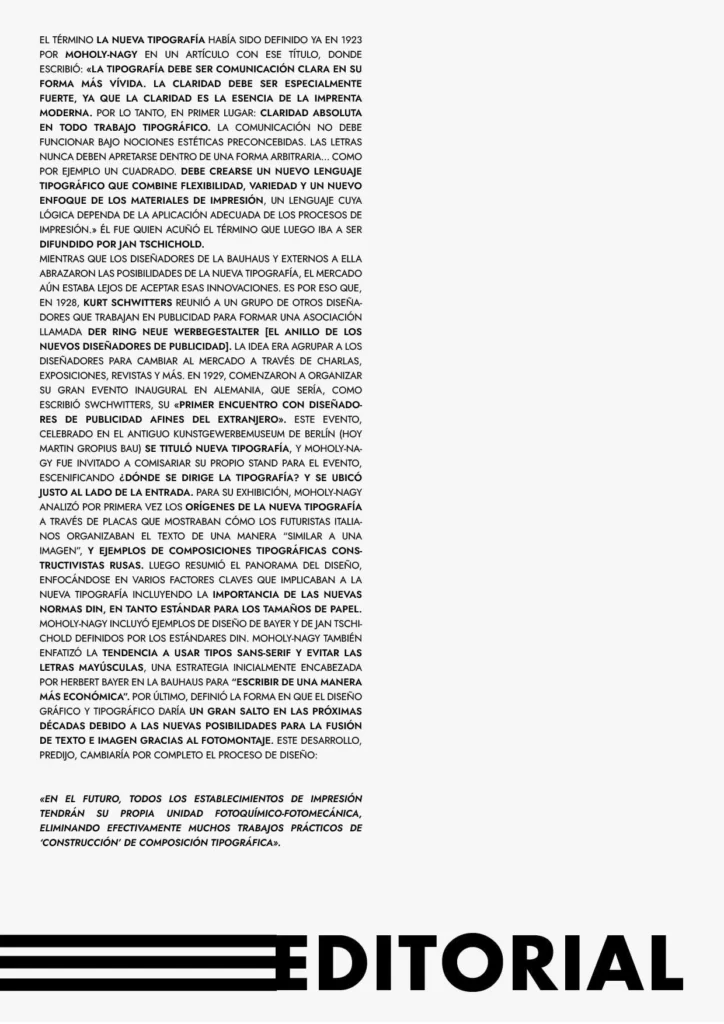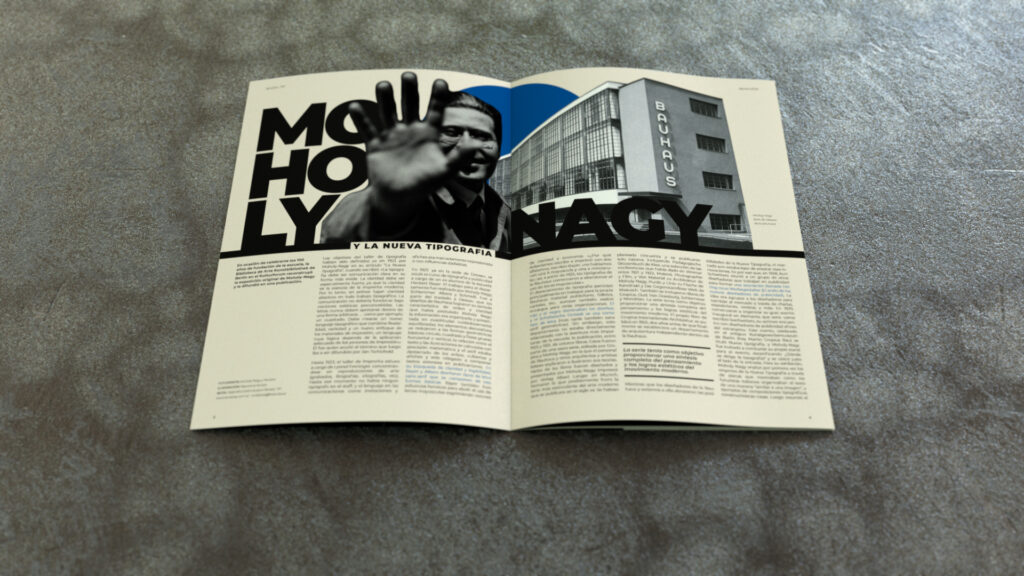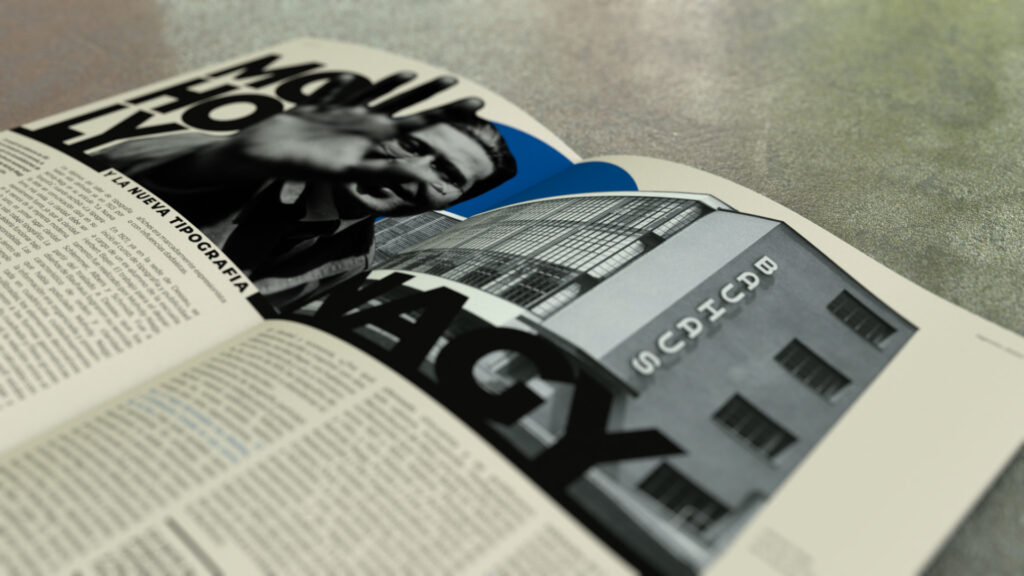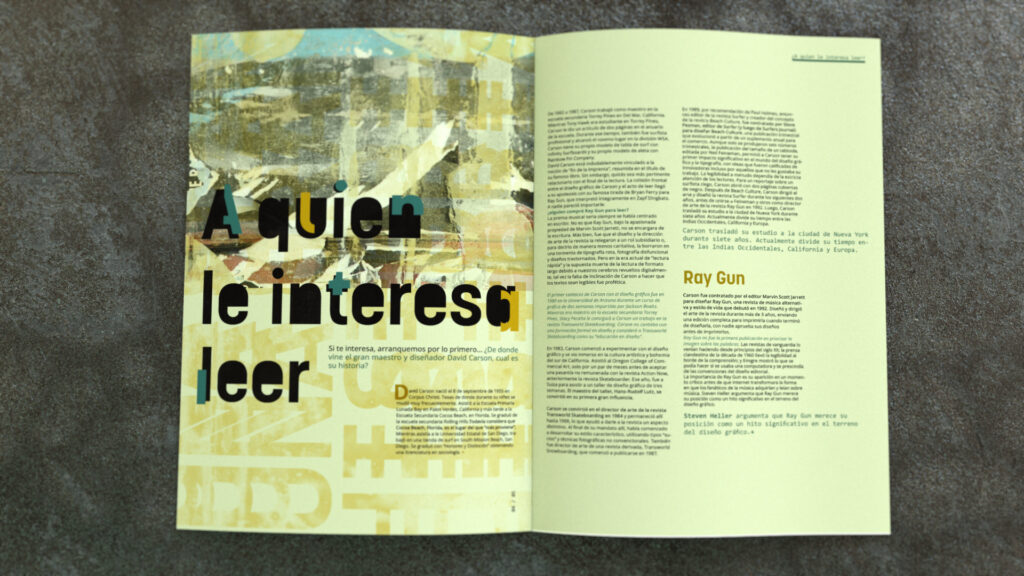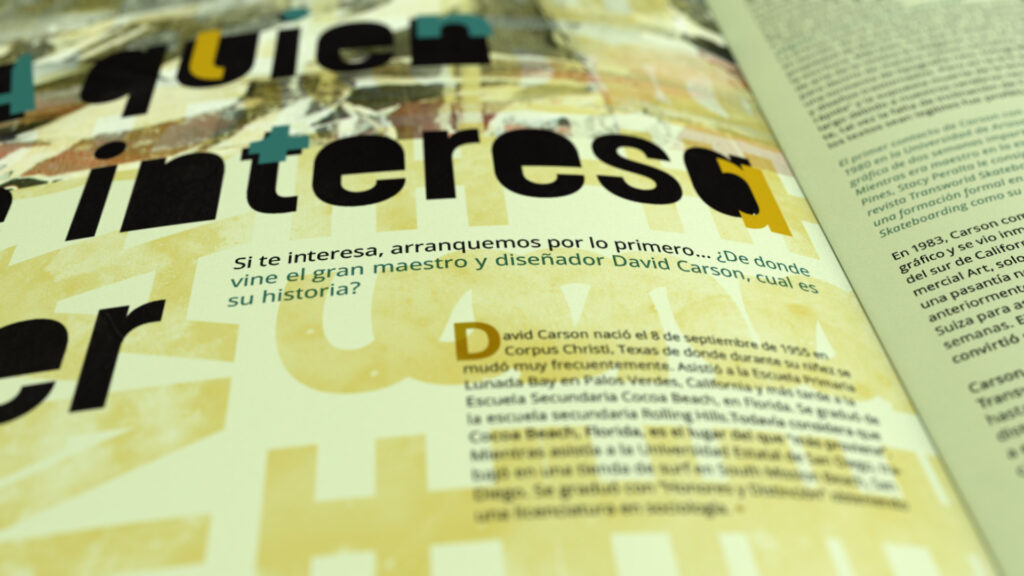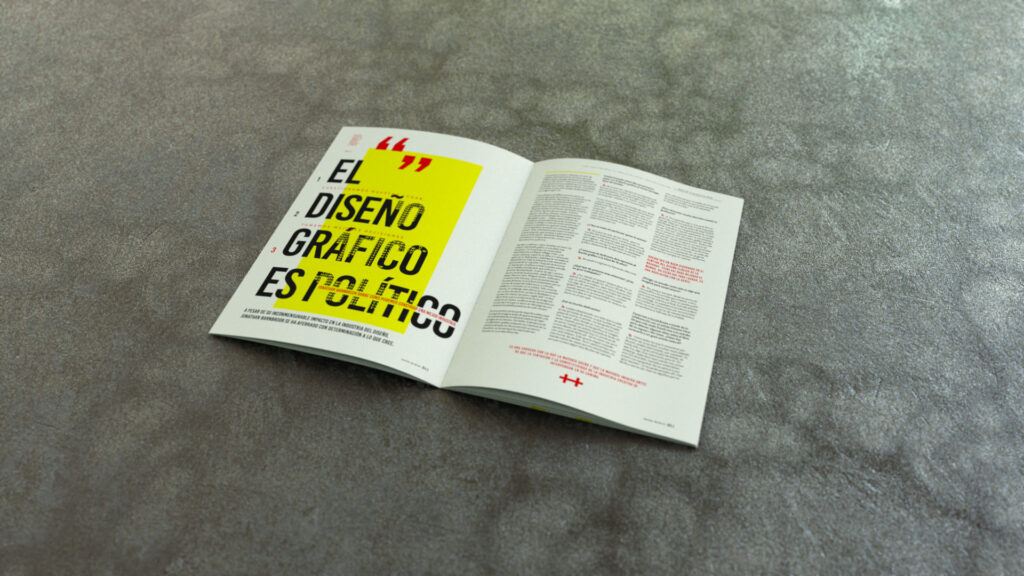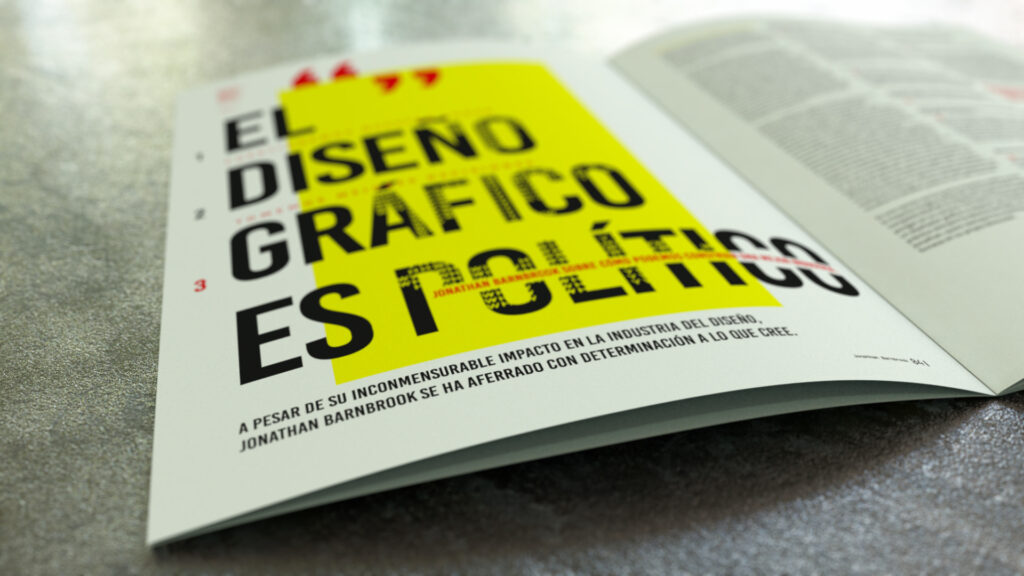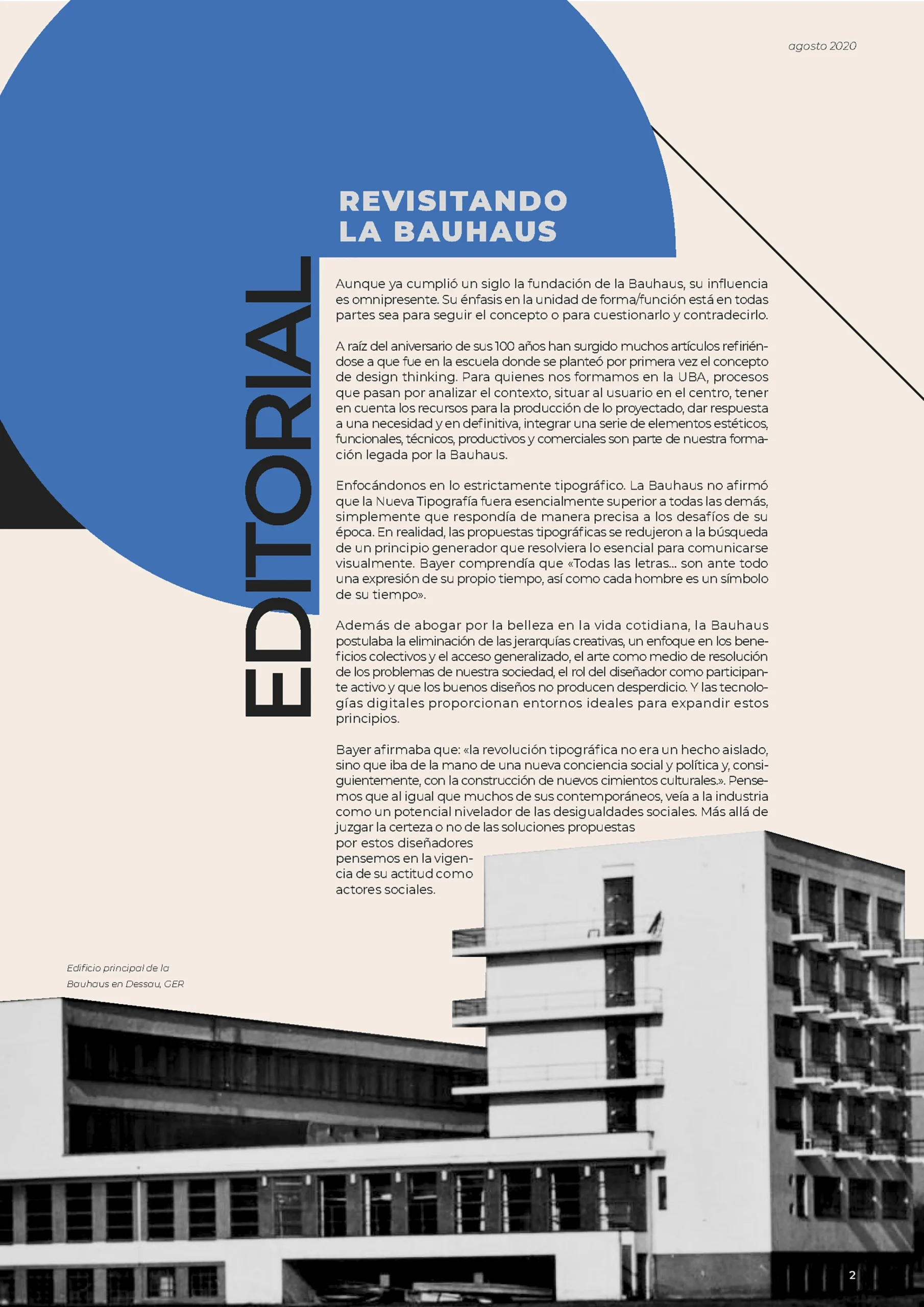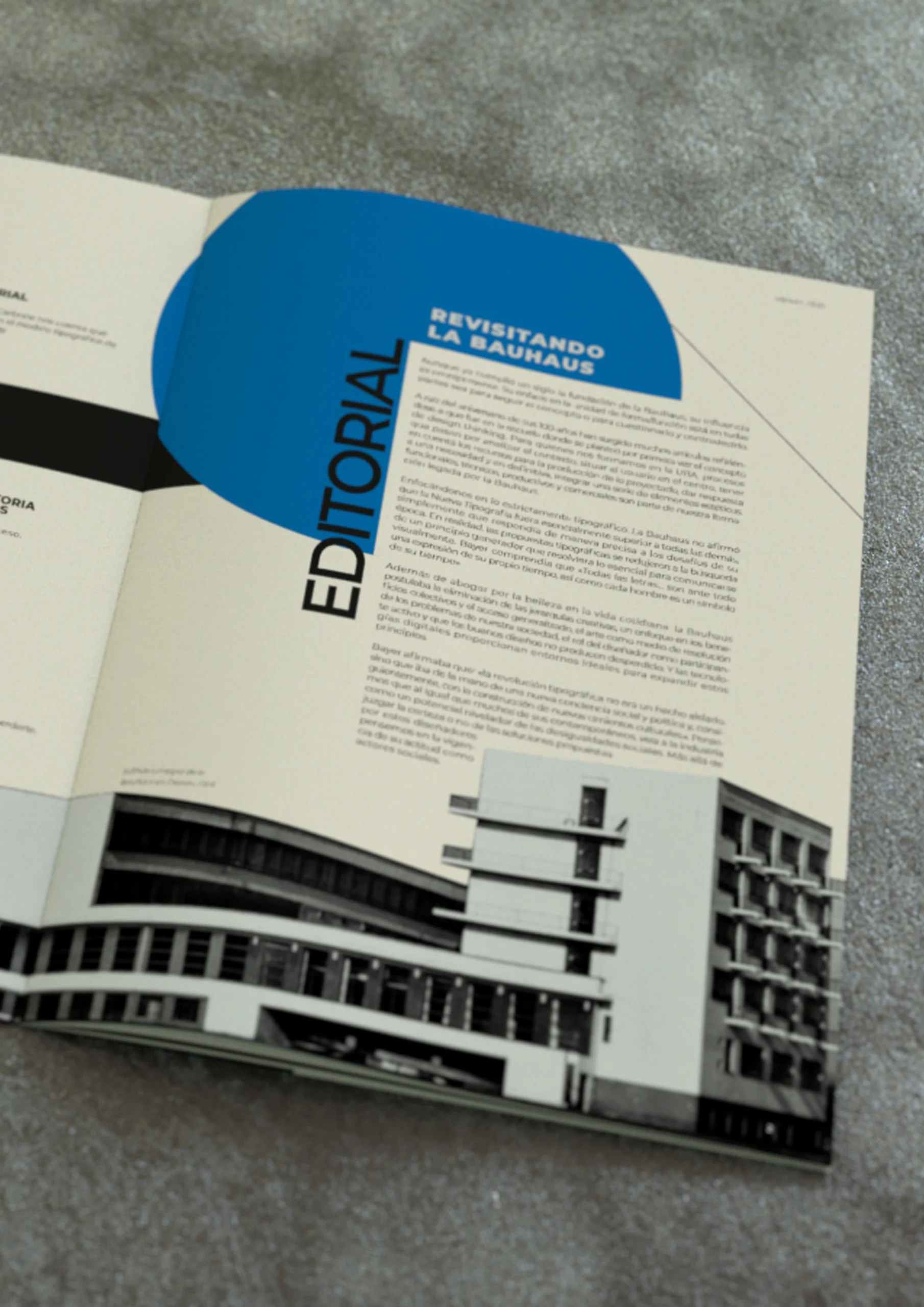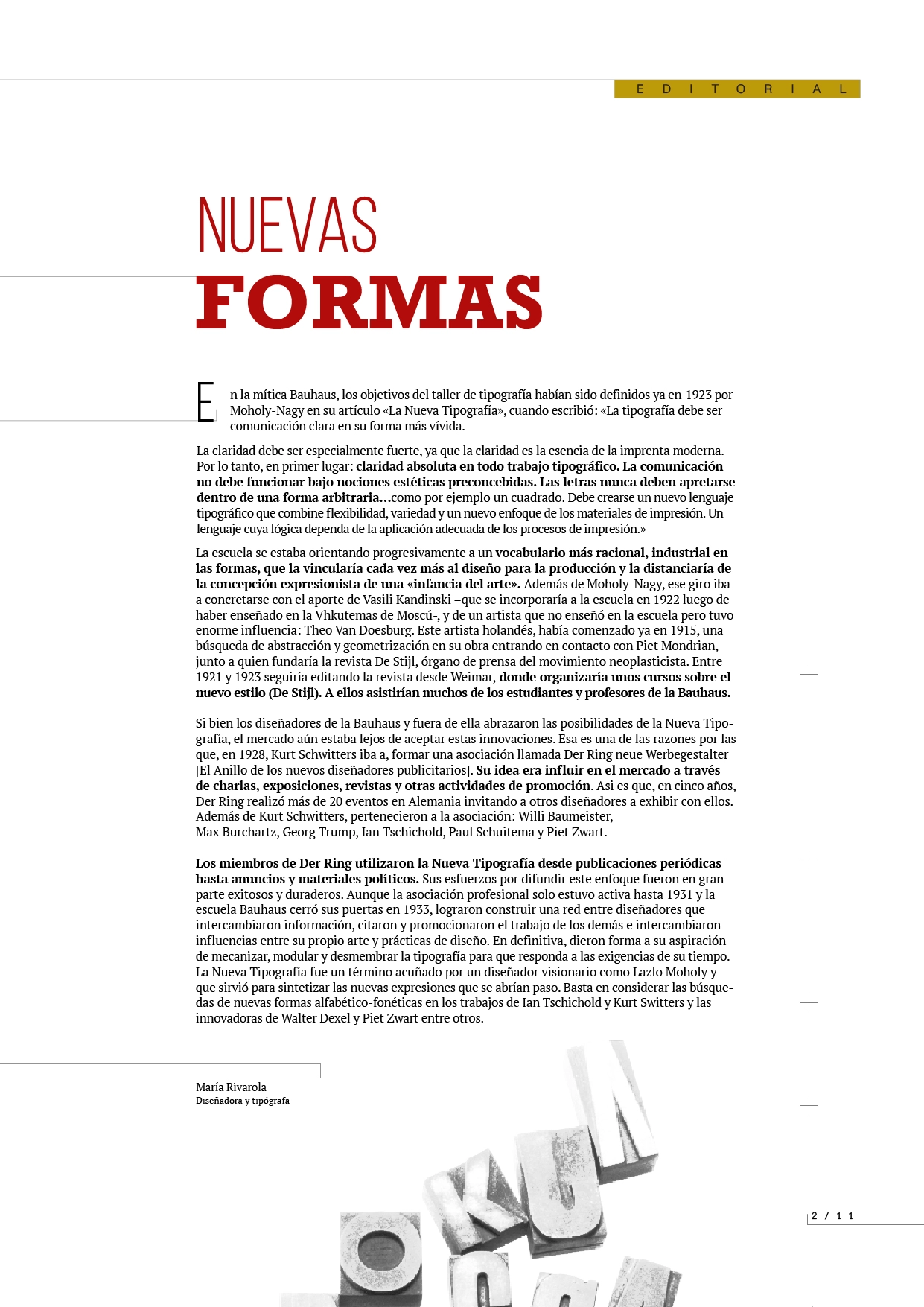
En este artículo nos concentraremos en desarrollar los aspectos que hacen al proyecto de una revista, las distintas tipologías textuales y los mecanismos de lectura.
Formato y frecuencia
Un diseño editorial se inicia con la selección del formato (o formatos) más apropiados para publicar su contenido. Antes del siglo XXI, la mayoría de las publicaciones periódicas existían en un solo medio: el contenido se imprimía o se publicaba digitalmente. En la actualidad es igual de probable que el material de una publicación aparezca simultáneamente en formato impreso, en un smartphone, en una tablet y en un sitio web. El tipo de contenido, la frecuencia de publicación y las expectativas de los lectores influyen enormemente en qué, dónde y cómo publicamos.
Así como no existe una única forma de imprimir, las pantallas no son universales. Si bien técnicamente su variedad es infinita, los formatos impresos comunican una gran variedad de contenido y a menudo responden a las limitaciones de la impresión, la distribución y la visualización. Y aunque las pantallas pueden estandarizarse, las diferencias en tamaño físico, proporción y resolución de pantalla (píxeles por pulgada) presentan docenas de posibles impresiones. Repasamos algunas posibilidades de formatos en el artículo Tipografía y diseño editorial.
La segunda condición que define una publicación es lo temporal. La frecuencia de publicación determina el tiempo dedicado al diseño y la edición de cada número y refleja cómo lo asimilarán los lectores. Las secciones de periódicos y las plataformas verticales de sitios web comunican a través de su diseño si un artículo es novedoso y actual (es decir, breve y de lectura rápida, producido en el día o la semana) o de mayor alcance (es decir, más extenso, con más contenido en texto e imágenes, creado con mucha antelación).
El diseño comunica su intención a través de la estrategia del contenido y de la identidad. La estrategia de contenido dicta qué aparecerá, cuándo y según qué criterios.
La identidad es clave como tarea del diseñador y se vuelve crucial cuando una publicación es un conjunto de transmisiones que no aparecen juntas en el mismo lugar y al mismo tiempo. ¿Qué acompañará siempre al contenido? ¿Tiene el contenido una voz editorial específica que lo distinga del contenido de otras publicaciones? Y cuando el contenido con diferentes horarios aparece en el mismo lugar, ¿cómo se identifica visualmente su carácter?
Funciones del texto
MARCA. Lo primero que establece una publicación nueva es el mensaje de marca, las señas identidad, la expresión y las sensaciones que se desean transmitir. Como veremos más adelante, esa identidad reside en el estilo visual que se desarrolla a lo largo de toda la publicación. Pero el núcleo de esa identidad está representado por la marca que aparece en la portada.
El logotipo de una publicación es el primer y más importante elemento de la portada y debe representar el carácter y la actitud hacia los lectores.
Visualmente es un elemento permanente aunque encontramos muchos ejemplos en los cuales se ha jugado con el logotipo haciéndolo interactuar con la foto de tapa o cono los titulares de tapa. Un ejemplo extremo es la publicación de La luna de Metrópoli que por tratarse de un suplemento de una diario cuenta con menos compromiso de estabilidad visual con respecto a la portada.
SLOGAN o TAGLINE. Algunos casos periódicos y revistas tienen un slogan o un tagline. Ubicado junto al cabezal de la publicación comunican al lector la índole de los contenidos. En el ejemplo, la resi’on de la revista Wired para Reino Unido que durante un tiempo uso un tagline o bajada.
TITULARES DE PORTADA. El contenido, la utilización y la ubicación de los titulares de portada son determinados generalmente por el director, si bien suelen atender a condicionamientos de marketing y competitividad. A menudo se ubican en el tercio izquierdo de la portada para asegurar su visibilidad. Pero la apariencia visual de estos titulares son responsabilidad del diseñador y es importante como juegan en la composición de la portada.
TÍTULARES DE NOTA [1]. Son vitales en la eficacia de la comunicación su ubicación y tratamiento.
COPETES O ENTRADILLAS [2]. Llamamos así al texto introductorio que adelanta el contenido de la nota. Frecuentemente, y en razón a cómo leemos, es más importante que el título al que sucede ya que informa contextualizando y resumiendo el contenido. Desde el punto de vista visual es un puente que vincula titular con el cuerpo del texto.
SUBTÍTULOS [3]. Pueden interrumpir textos densos y son especialmente útiles cuando se trata de artículo extenso. En algunas ocasiones esas señales que indican partes diferenciadas del contenido pueden ser simplemente números o iniciales que indican el comienzo de una nueva sección.
DESTACADOS O ENTRESACADOS [4]. Son sumamente útiles porque al fragmentar el cuerpo del texto, facilitan la lectura y generan un tono más atractivo.
CRÉDITOS Y PIES DE AUTOR [5]. Su tratamiento varía según la importancia que tengan los autores para la publicación. Los periódicos generalmente no incluyen el nombre del autor.